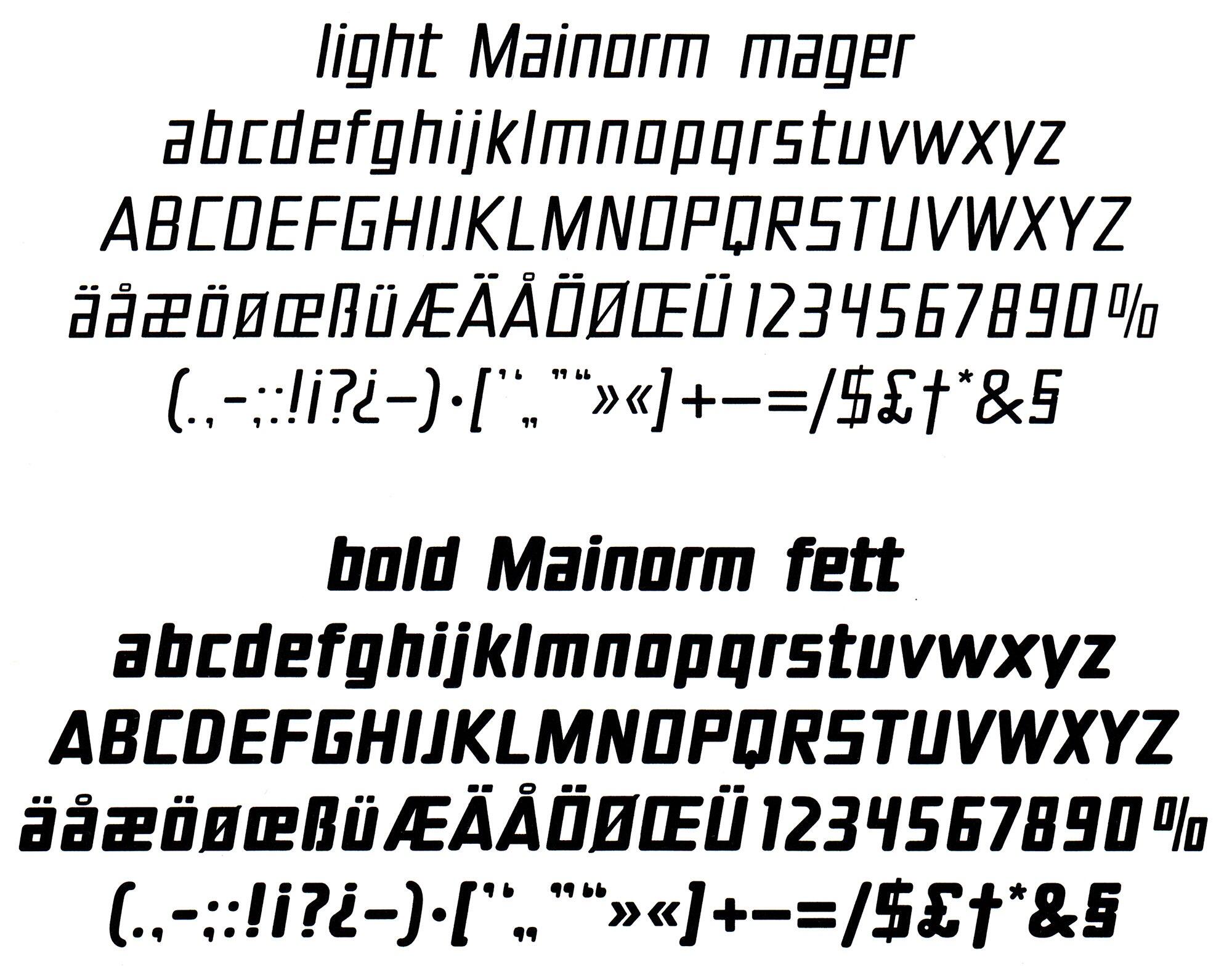
Die Mainorm, benannt nach ihrem Gestalter Karl-Heinz Maireder, erschien in den 1980er-Jahren als Fotosatzschrift bei der H. Berthold AG. Die beiden Strichstärken sind heute mit westeuropäischer Zeichenbelegung über Monotype erhältlich.